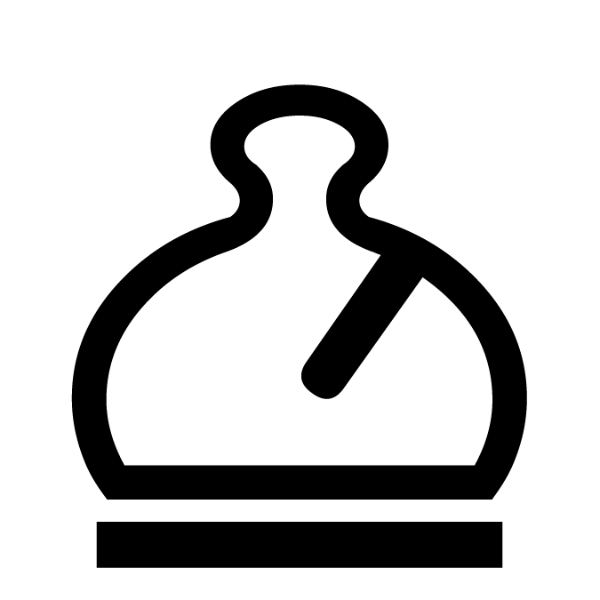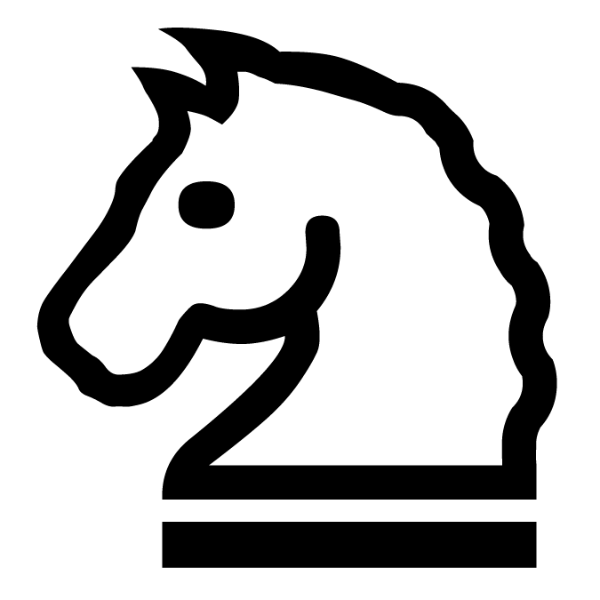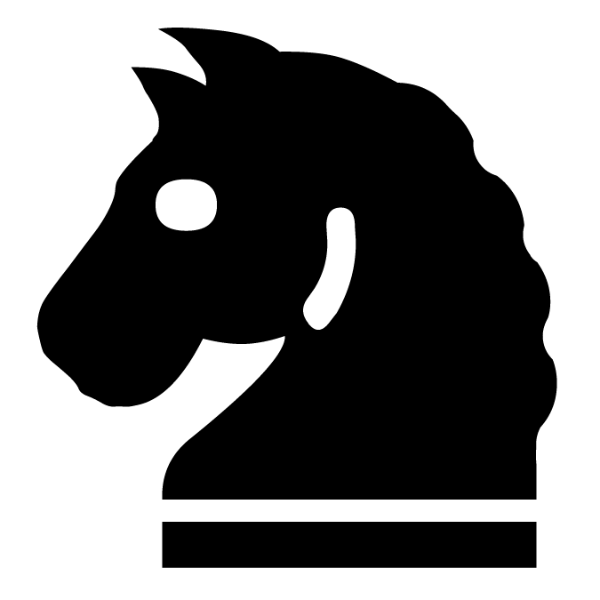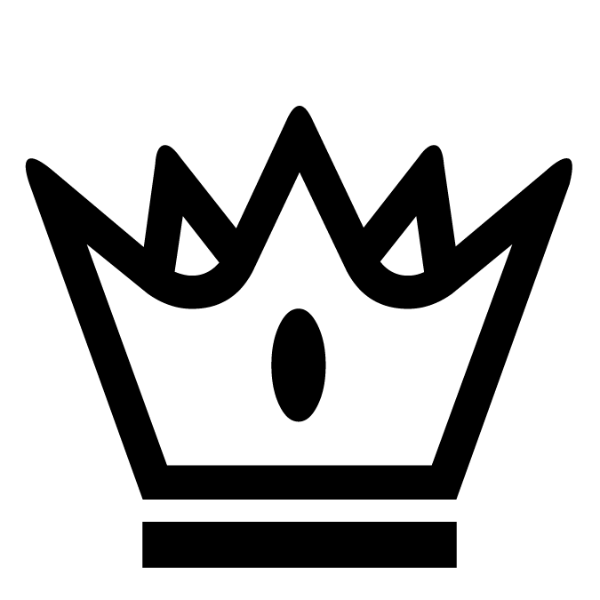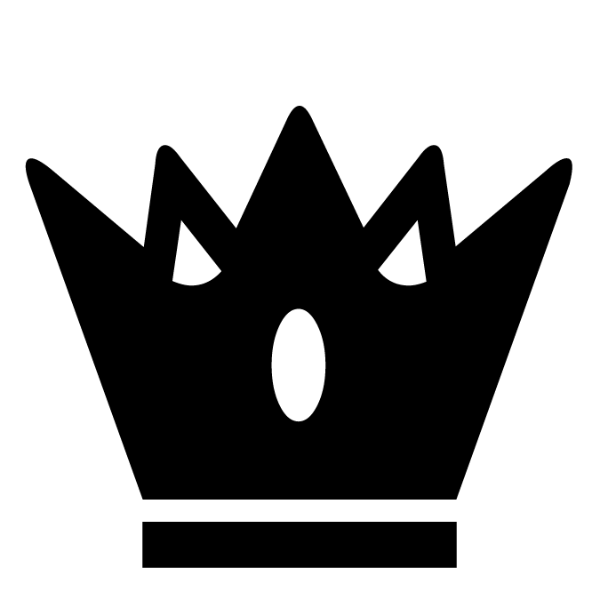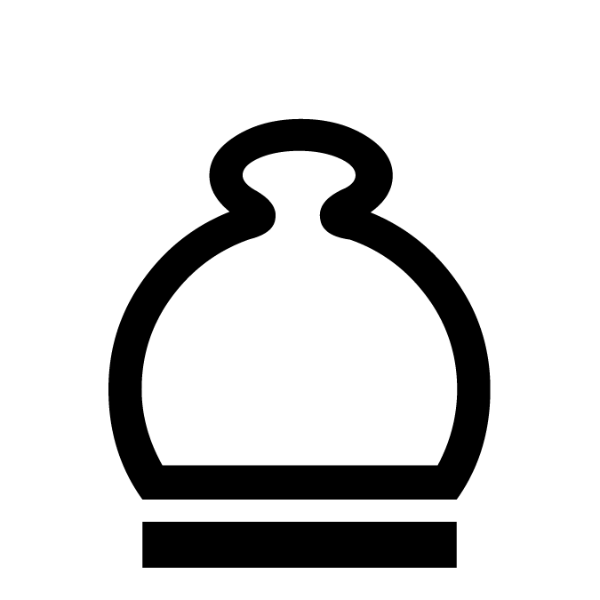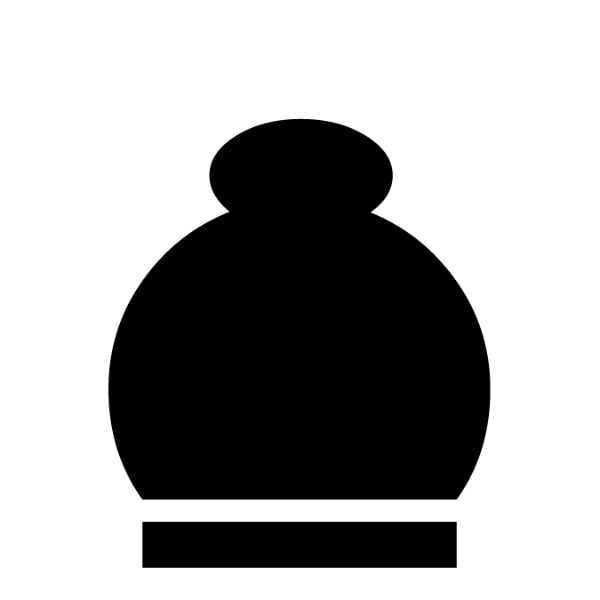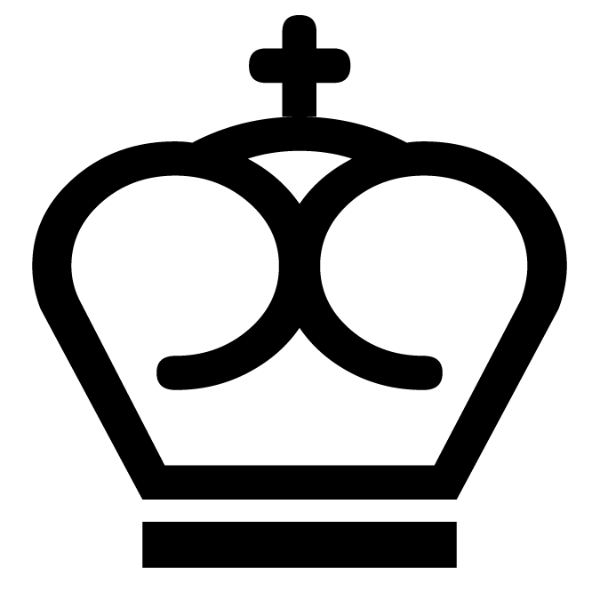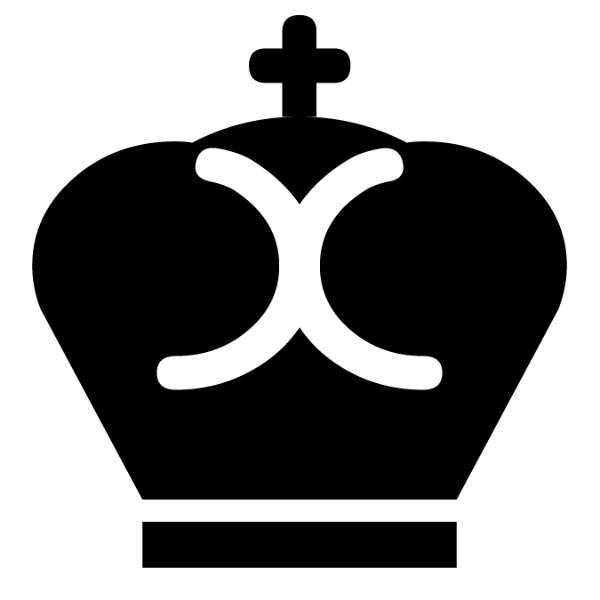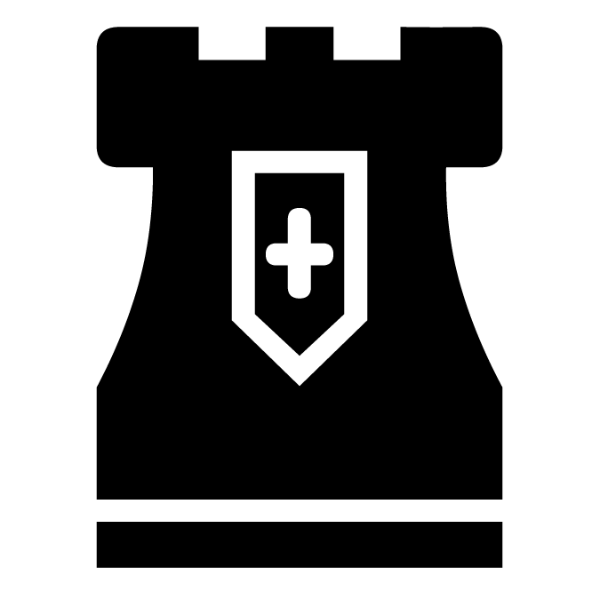
La Fuente Chess Motif destaca por su estilo sobrio y las formas abombadas de piezas clave como el rey, el alfil y el peón, dando un aspecto único y elegante. Además, la torre se presenta con un diseño grande e impetuoso, convirtiéndola en la protagonista de esta fuente.
Juego de Ajedrez con la Fuente Motif: